Зачем подходить к выбору шрифта для мемов с умом?
- Чтобы не исказить смысл мема;
- Чтобы поддержать визуальный образ бренда или проекта;
- Чтобы придать мему нужную эмоциональную окраску;
- Чтобы сообщение дошло до пользователя.
Разберёмся, как добиться этих целей и выбрать лучшие шрифты для мемов.
Как выбрать правильный шрифт для мемов?
Шрифт в меме выполняет не только эстетическую, но и смысловую функцию. Вот ключевые аспекты, которые следует учитывать, чтобы подобрать лучший вариант:
- Читабельность. Это самая очевидная и в то же время самая важная задача, которой часто не уделяют должного внимания. Но ведь именно от читабельности шрифта зависит, дойдёт ли сообщение, передаваемое через мем, до пользователя. Шрифт должен хорошо считываться даже в низком разрешении или при использовании на неоднородном фоне. Подробно о том, как выбрать шрифт, который будет хорошо читаться, мы рассказывали здесь.
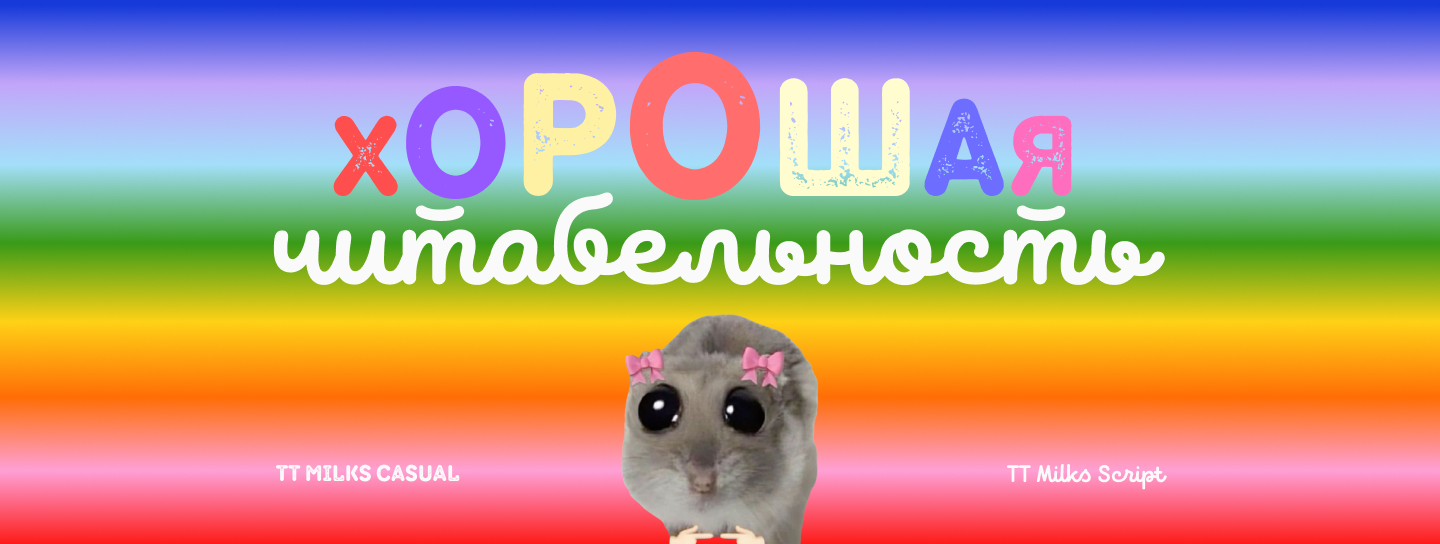
- Оптимальный размер и жирность. Слишком мелкий или тонкий шрифт будет теряться, а слишком большой и жирный — отвлекать на себя внимание. Важно, чтобы текст гармонично взаимодействовал с картинкой и все элементы дополняли, а не перекрикивали друг друга.
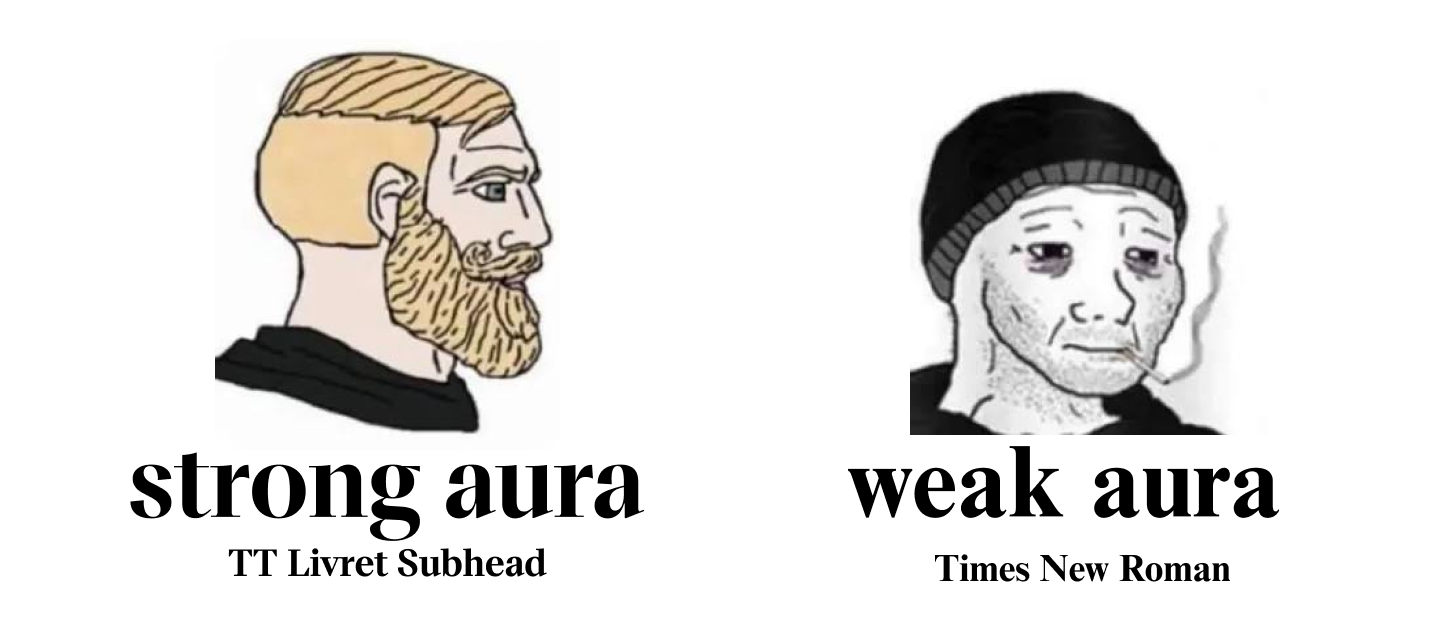
- Эмоциональный тон. Разные шрифты несут в себе разное настроение: они могут быть весёлыми, серьёзными, агрессивными или спокойными. Важно, чтобы шрифт отражал или подчёркивал суть вашего мема.
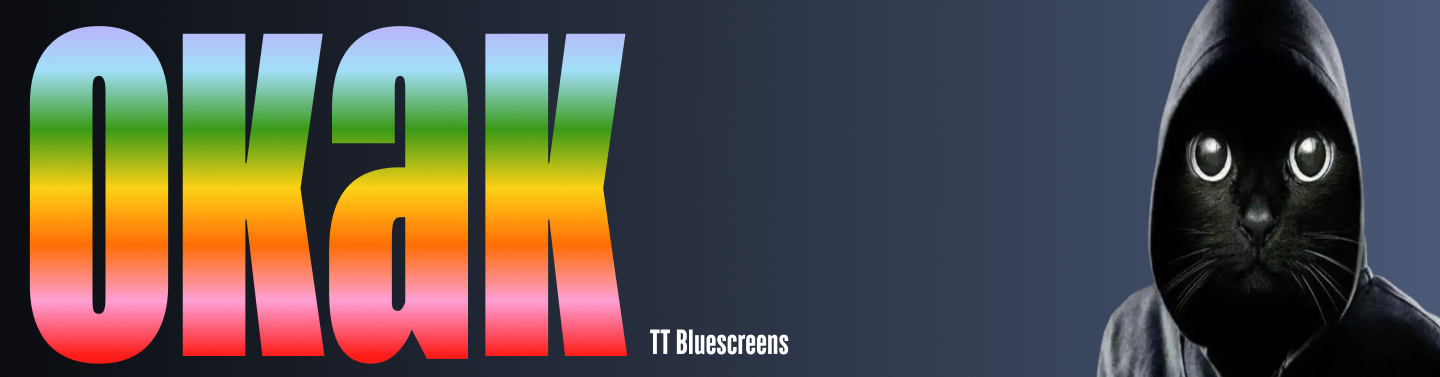
- Контекстная уместность. Например, использование элегантной антиквы в ироничном меме создаст контраст между формой и содержанием.
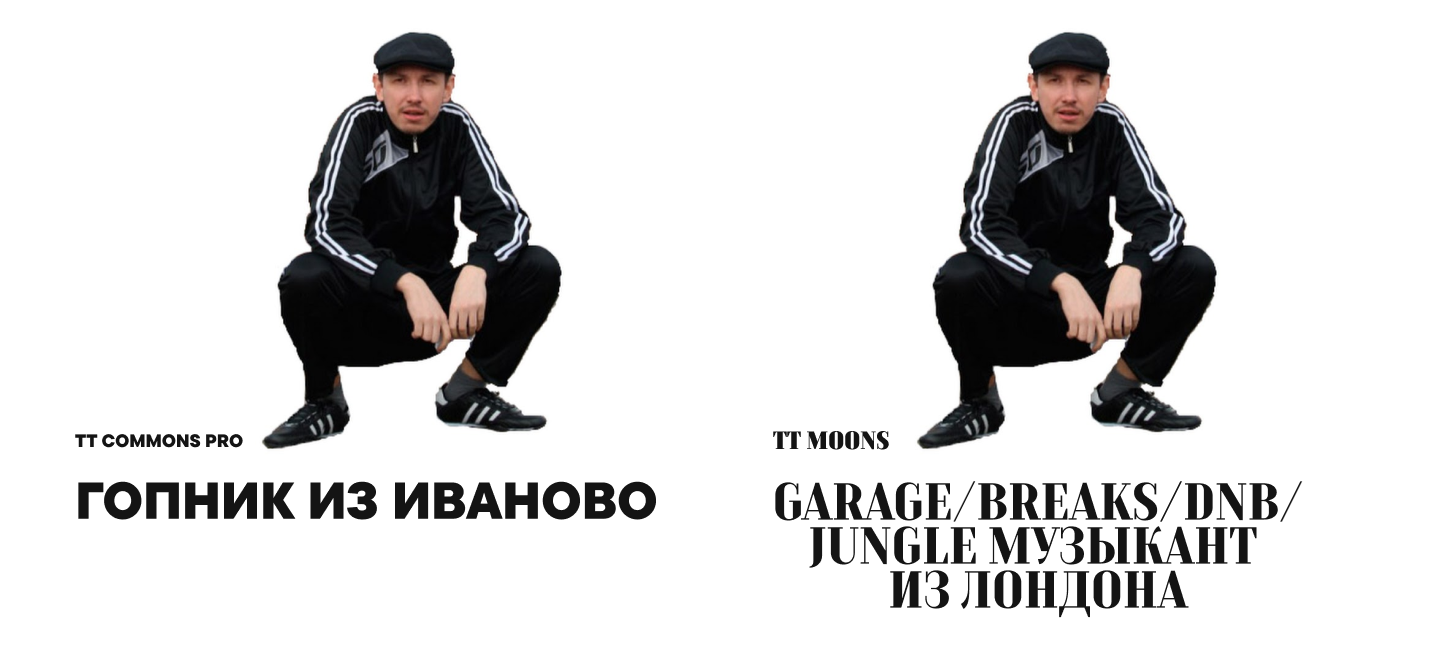
- Минимализм. Избыток декоративных элементов отвлекает от сути. Чем проще форма, тем быстрее и легче считывается сообщение.
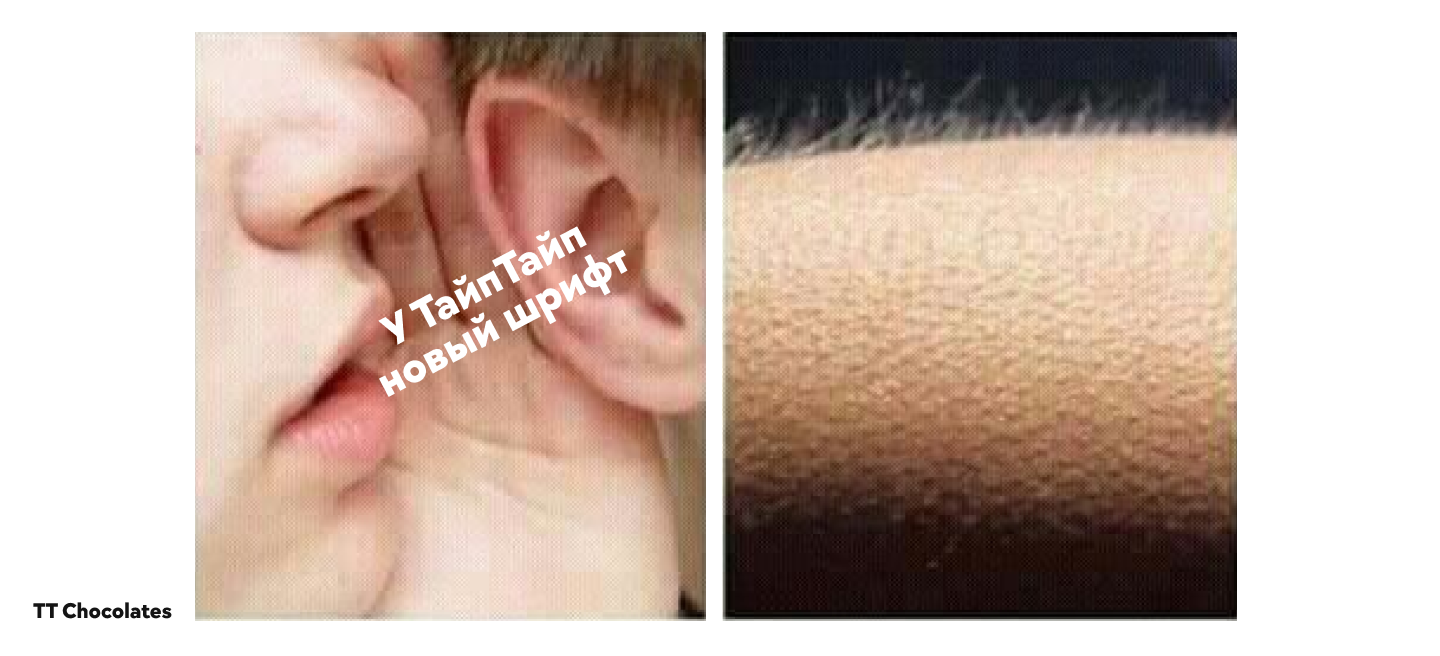
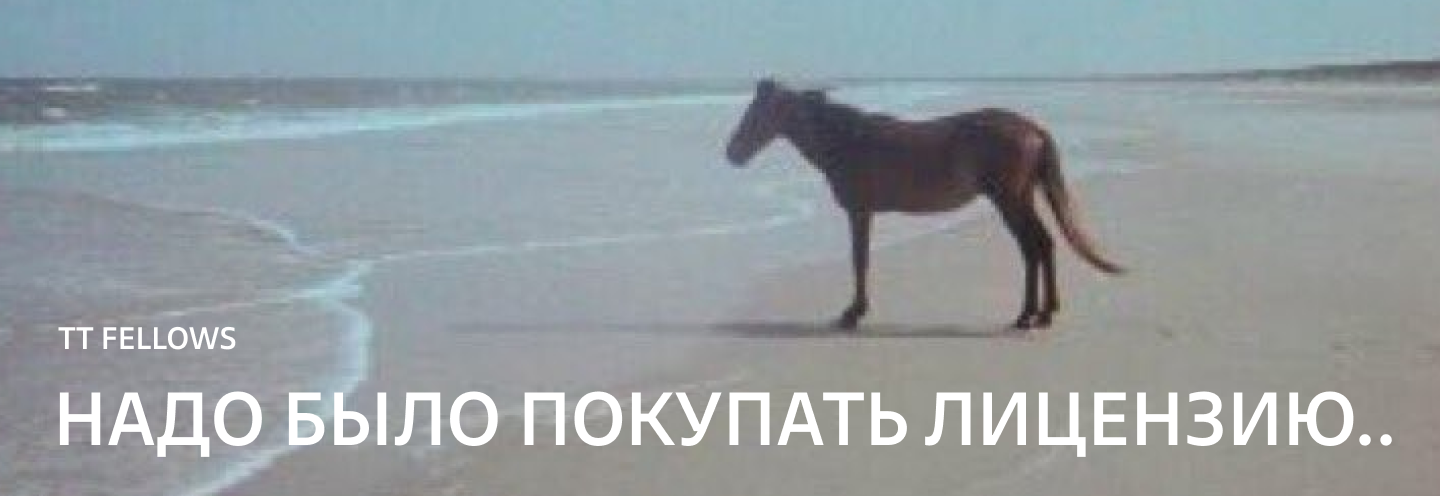
Что будет, если выбрать неправильный шрифт для мемов?
Ошибки в выборе шрифта для мемов, конечно, не приведут к катастрофическим последствиям, однако могут поспособствовать тому, что ваш мем останется незамеченным и не вызовет нужного эффекта.
Вот некоторые из возможных проблем:
- Потеря воздействия. Текст на меме, набранный слишком тонким и мелким шрифтом, будет восприниматься как сноска и останется либо вовсе не прочитанным, либо оторванным от контекста.
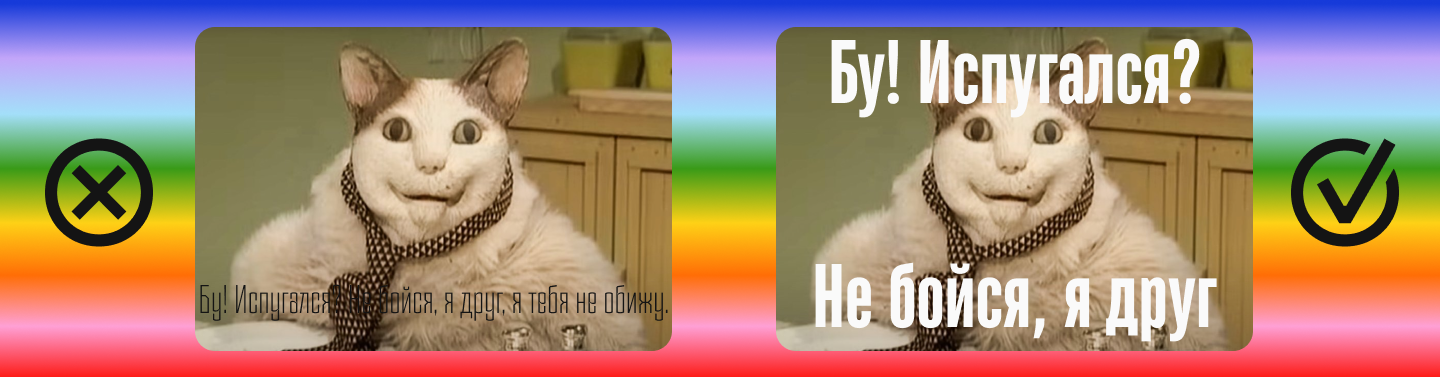
- Несоответствие тона. Мягкий и романтичный в агрессивном меме создаст диссонанс и превратит сарказм в неловкую попытку казаться милым.
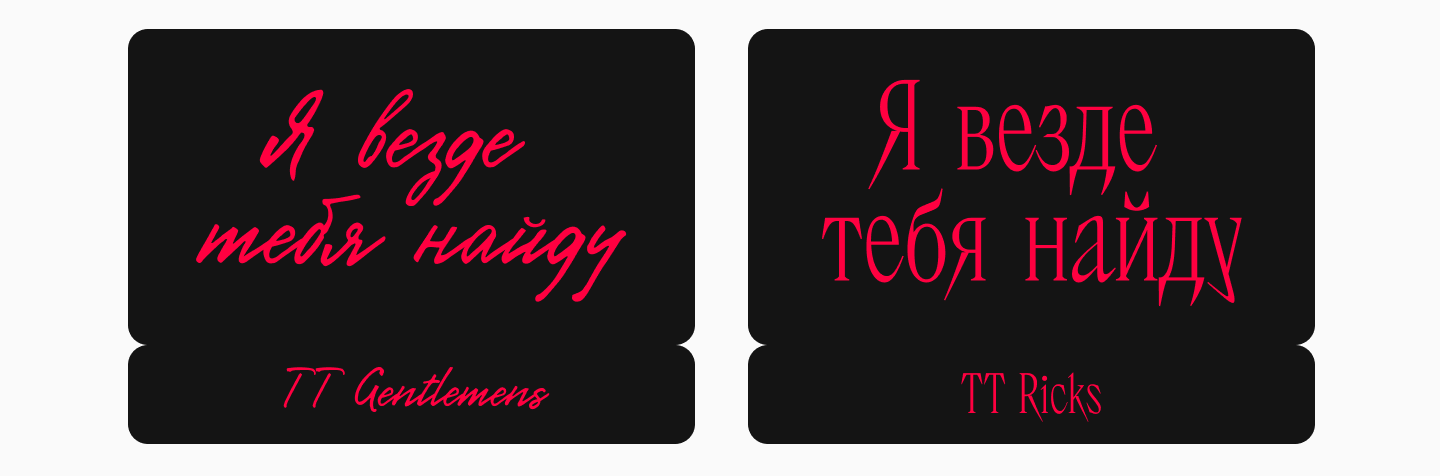
- Деконструкция смысла. Если в меме про IT-специалистов используется рукописный шрифт, шутка теряет связь с контекстом и воспринимается как случайный набор слов.
- Архаичность. Если использовать устаревшие шрифты, сам мем тоже рискует показаться неактуальным. Пользователь может подумать, что этому мему уже много лет, и не станет делиться им с друзьями.
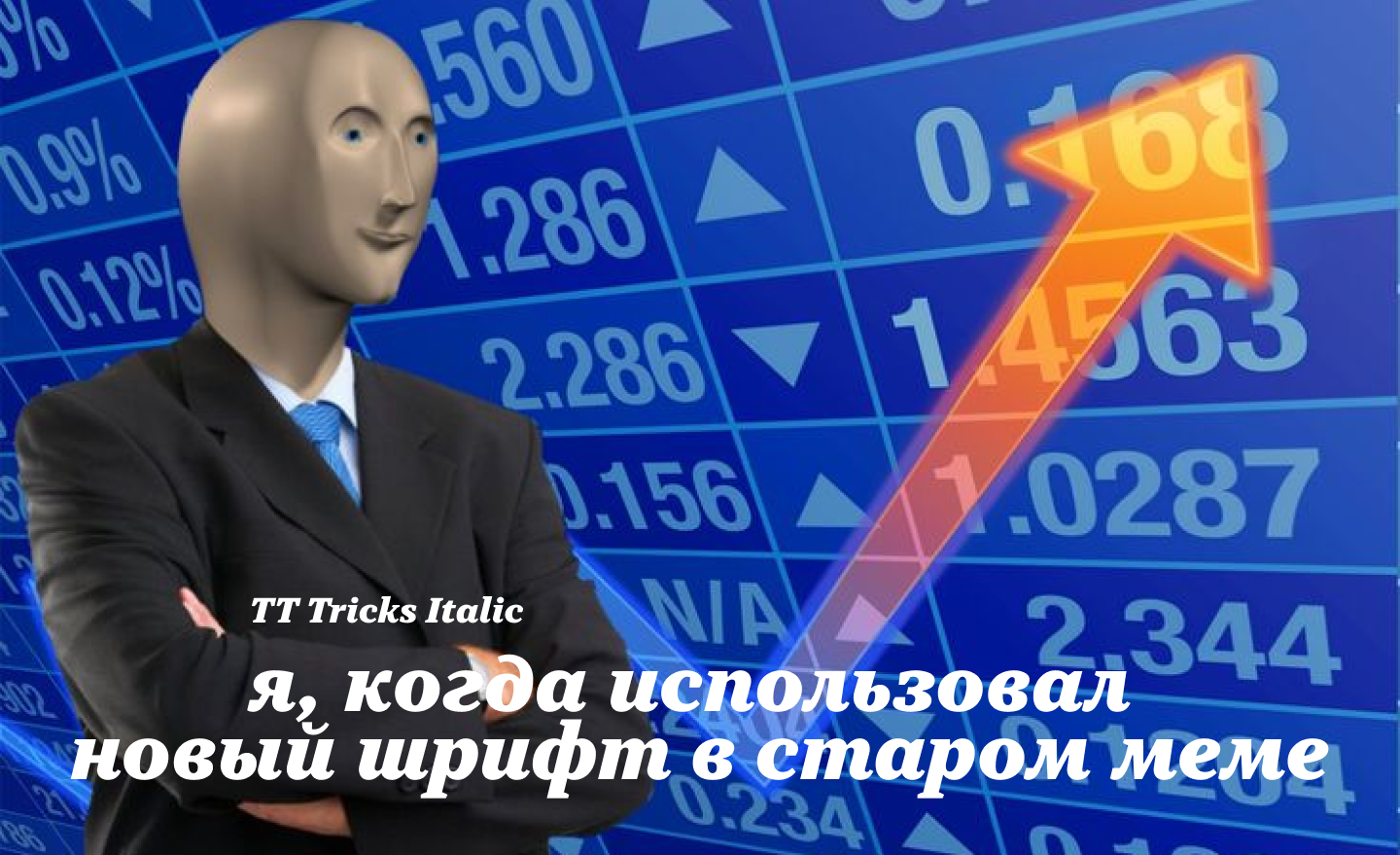
Какой шрифт, используемый в мемах, самый популярный?
Самым популярным шрифтом для мемов считается Impact — гротескный шрифт без засечек, созданный в 1965 году Джеффри Ли. Его ключевая особенность — экстремально жирное начертание и узкие межбуквенные промежутки, благодаря чему текст выглядит плотным и мощным.
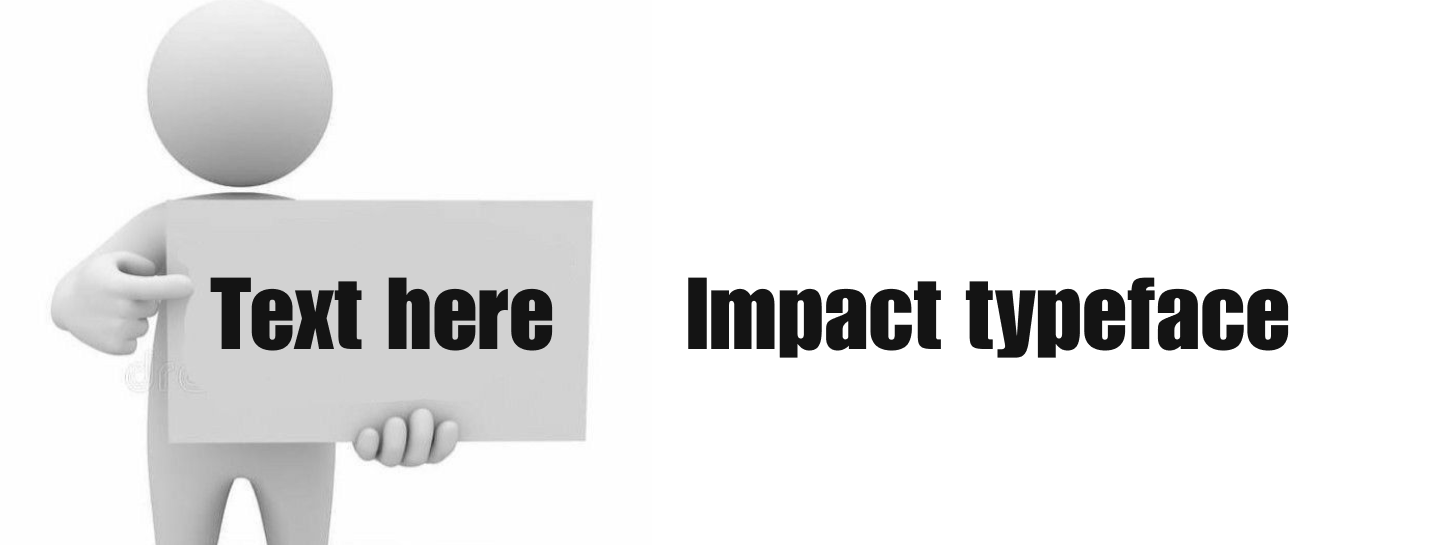
Но почему же Impact стал «королём мемов»? Давайте разберёмся.
Первый фактор — его визуальные характеристики. Узкие пропорции позволяют вмещать больше текста на небольшой площади, а достаточная жирность привлекает внимание. При этом благодаря простым формам шрифт отлично читается в коротких надписях и остаётся различимым даже на детализированном фоне.
Характер Impact можно назвать уверенным и даже слегка агрессивным, благодаря чему он отлично вписывается в контекст большинства мемов, а также усиливает провокационный или комический эффект — он не «говорит», а «кричит».
Не менее важный критерий успеха Impact — его доступность. Шрифт входил в базовый набор Core Fonts for the Web, предустанавливался в Windows и был доступен на macOS при установке дополнительных пакетов, таких как Microsoft Office, что делало его универсальным инструментом для создателей контента.
Более того, первые генераторы мемов (например, Quickmeme, Meme Generator) использовали Impact как шрифт по умолчанию, закрепляя его как часть визуального языка жанра.
Однако, несмотря на свою популярность, Impact уже стал архаизмом и символом определённой эпохи. Чем же его заменить? Рассказываем ниже!
Актуальные альтернативы популярным шрифтам для мемов
В этой подборке мы предлагаем актуальные альтернативы Impact и другим популярным шрифтам для мемов. Они позволят сделать ваш мем оригинальным и свежим, не отходя от привычной визуальной эстетики.
TT Bluscreens Black вместо Impact
Среди графических особенностей Impact — максимальная насыщенность и узкие пропорции — буквы «прижаты» друг к другу, что создаёт эффект монолитности.
Похоже и в то же время гораздо более стильно и современно выглядит TT Bluescreens — неогротеск с узкими пропорциями. Это шрифт со спокойным, но в то же время запоминающимся характером, который привлечёт внимание, будет хорошо читаться и позволит уместить больше символов в небольшое поле.
Заключение
Шрифт в меме — это инструмент управления вниманием. Грамотный выбор усиливает эффект, а случайно подобранный вариант может исказить смысл или вовсе не донести сообщение до пользователя. Если сомневаетесь, попробуйте провести A/B-тестирование: вы увидите, что отклик на один и тот же мем будет разным в зависимости от шрифта.